Cómo personalizar tus fuentes de Instagram [Manera fácil]
Afortunadamente, sus fuentes de Instagram personalizadas no se encuentran entre ellas.
Esas divas e influencers que usan fuentes elegantes en sus biografías de Instagram no tienen ningún secreto que el resto de nosotros nunca sepa. Simplemente usan las herramientas y aplicaciones (¡gratuitas!) que cambian las fuentes de Instagram. Instagram nativo no te da muchas opciones, pero eso no significa que no haya opciones.
Empecemos con lo básico. Instagram Stories tiene algunas fuentes diferentes que puedes usar.
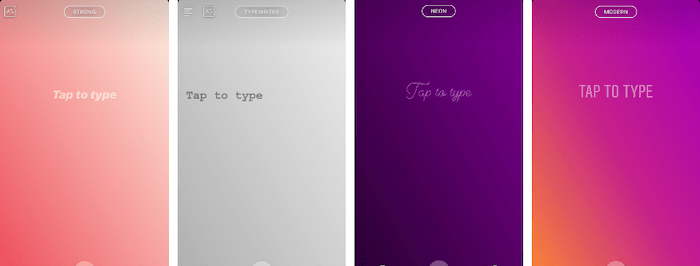
Sin embargo, Instagram regular, incluido su nombre, biografía, subtítulos y comentarios, solo tiene una opción.
Cambiar la fuente de Instagram puede ser una decisión personal o una elección de marca. Instagram en general es excelente para crear un portafolio de marca cohesivo, pero no poder hacer coincidir tus fuentes con tu estilo visual es un obstáculo para eso.
¿Cómo personalizo mis fuentes de Instagram? ¿Qué pasa con las fuentes bio de Instagram?
Te sorprenderá lo súper simple que es esto.
Ya sea que desee cambiar sus fuentes en su biografía, subtítulos y comentarios de Instagram o si desea personalizar sus Historias, lo tenemos cubierto.
Cambiar su fuente para Instagram: por qué y cómo
Como Instagram no viene con esto incorporado, usará una aplicación o herramienta de terceros para cambiar las fuentes de Insta.
La herramienta real que elija no importa tanto. No hay uno que sea particularmente mejor o peor que los demás. Algunos de los sitios web incluso tienen el mismo aspecto: compare LingoJam con las fuentes de Instagram, por ejemplo.
Con estas herramientas, una vez que esté satisfecho con el aspecto de su texto, simplemente copie y pegue en Instagram para actualizar su nombre, biografía, pie de foto o comentario.
Las mejores herramientas y aplicaciones en línea para cambiar sus fuentes IG
1) LingoJam: basado en la web
Tomé el título de mi última publicación de Instagram para jugar con LingoJam. Pegué el título en el cuadro de la izquierda y luego el cuadro de la derecha se completó automáticamente con las diferentes fuentes que podía usar.
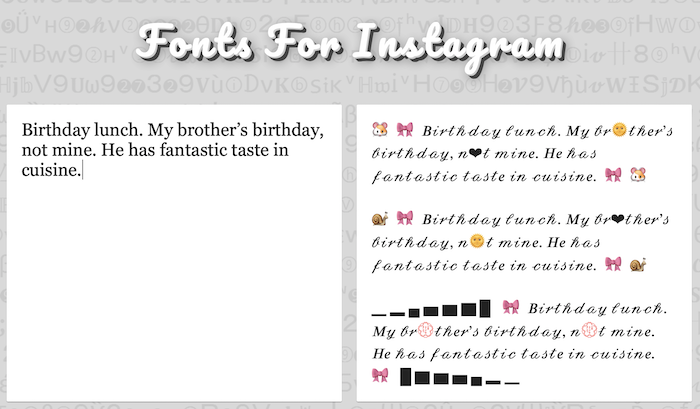
Había un montón de opciones; algunos eran tradicionales y otros eran creativos o... raros.
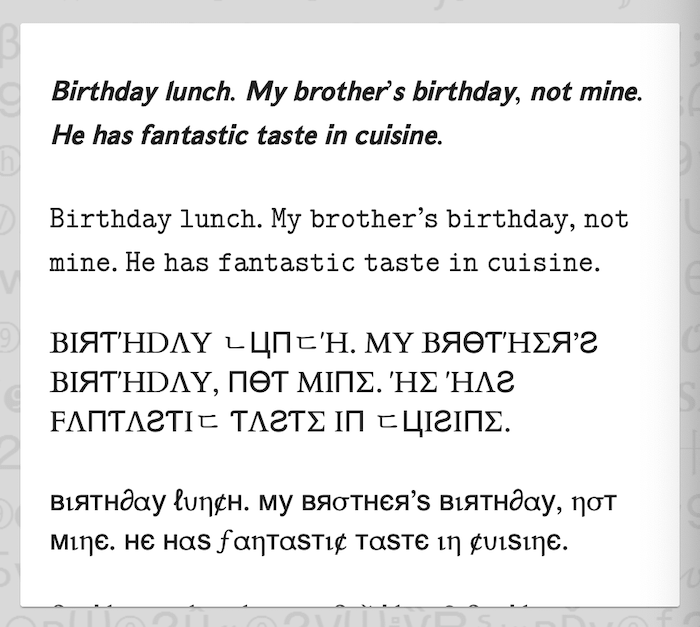
Elegí uno y lo copié/pegué como comentario en mi foto. Se veía igual en la aplicación.
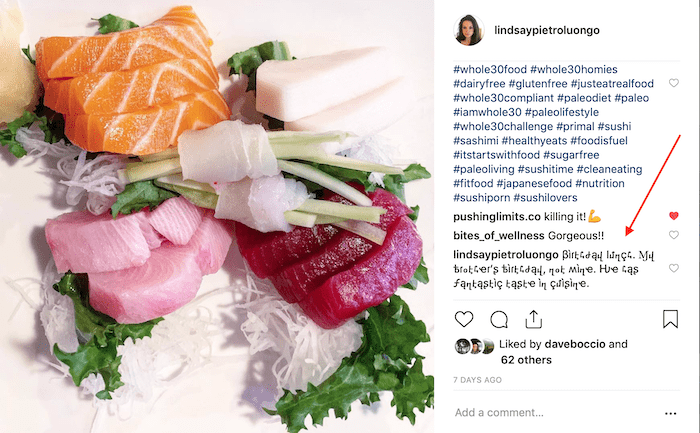
2) Fuentes de Instagram: basadas en la web
Las fuentes de Instagram funcionaron igual que LingoJam, y la selección de fuentes parecía la misma; puede haber algunas diferencias, pero nada me llamó la atención mientras me desplazaba.
Decidí cambiar mi biografía de Instagram usando el sitio web. Funcionó y se veía idéntico en línea y en la aplicación.
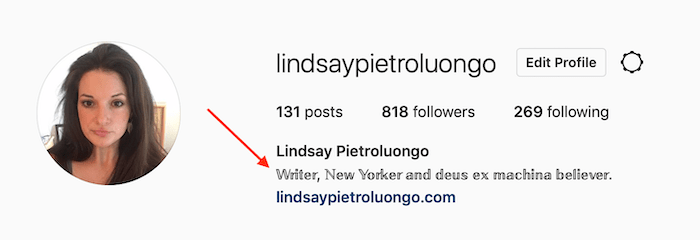
También cambié la fuente de mi nombre Insta:
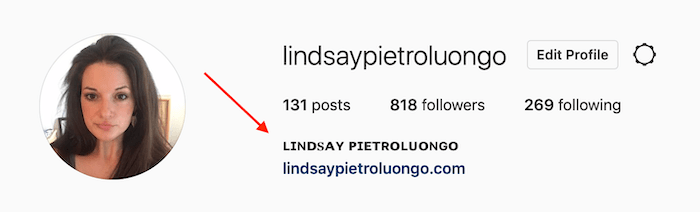
3) Mega Cool Text: basado en la web
Mega Cool Text tiene un conversor de letras chinas. Solo confiamos en que las letras sean precisas, pero se ven geniales y hay algunas opciones diferentes.
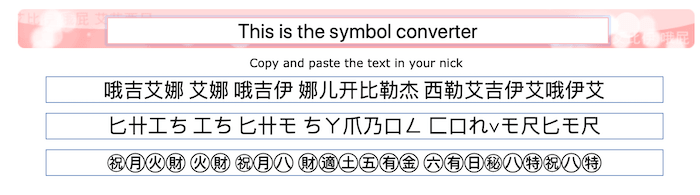
El problema con estos cambiadores de fuentes basados en la web es que es una molestia usarlos en su teléfono. Puede ir y venir de la URL en su teléfono, pero creo que usar una aplicación móvil es mucho más fácil.
4) Fuentes – para Instagram: aplicación móvil
Descargué la versión gratuita de 'Fuentes para Instagram' para ver si era más fácil de usar en mi teléfono que en los sitios web.
Con la aplicación, el proceso ocurre al revés: elige la fuente que desea y luego escribe el texto. Esto le permite crear texto que combina varias fuentes. También puedes agregar emojis.
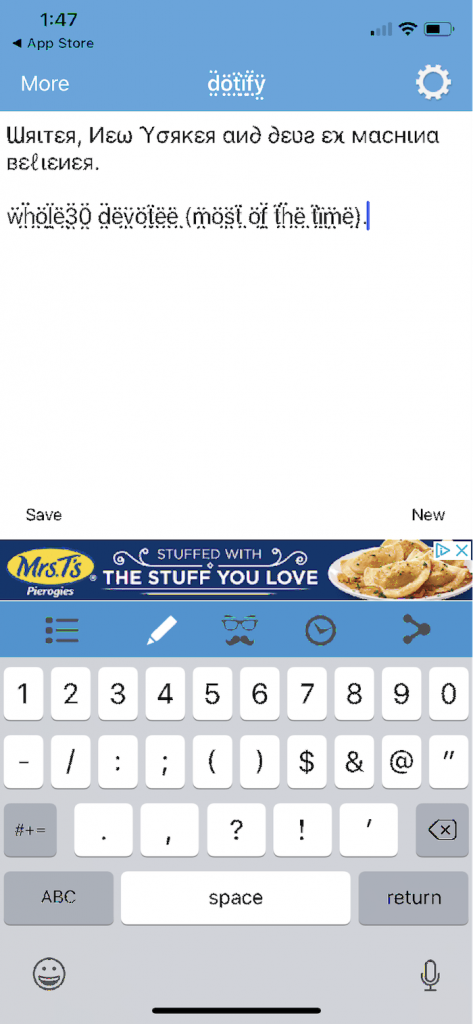
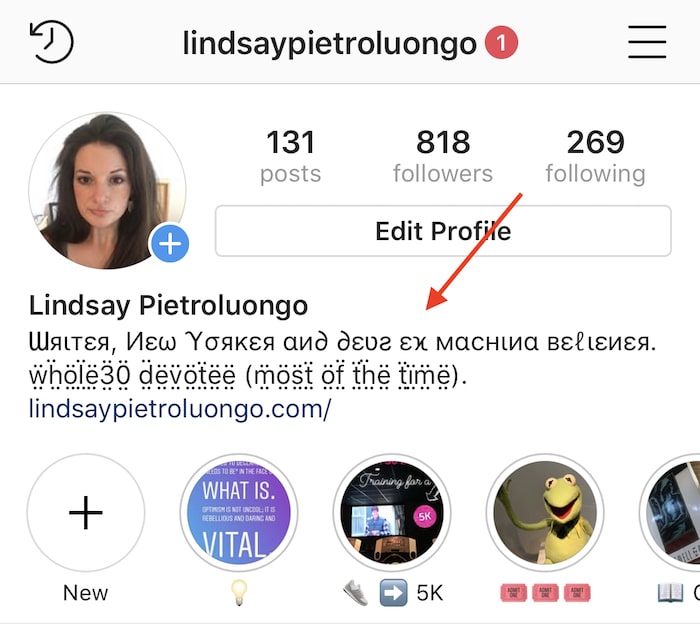
La ventaja de las aplicaciones móviles frente a un sitio web : son más intuitivas y menos complicadas de usar. También hay una forma más de acceder a esta funcionalidad, descargando una aplicación de teclado.
Ok, en otra aplicación Insta Fonts...
5) Sprezz: teclado personalizado
El teclado personalizado Sprezz es posiblemente el método más fácil para usar diferentes fuentes en Instagram, pero las opciones son muy limitadas. Sprezz es gratis y una vez que lo descargas tienes que actualizar tu configuración.
Luego puede elegir el teclado Sprezz cuando esté en Instagram tocando este símbolo:
Solo hay cinco opciones de fuente, pero solo elige tu favorita y luego la usas para escribir. Usé este estilo de fuente para cambiar mi biografía. Sin embargo, no salió en color como pensé que lo haría.
Cómo agregar símbolos a tu texto en tu biografía de IG
Digamos que desea agregar símbolos a su fuente pero quiere algo más que los emojis en su teclado. Dirígete a CoolSymbol.com en el navegador de tu teléfono, elige tu símbolo, haz clic en el botón de copiar a la derecha y luego pégalo en tu Instagram. (¡Se trata de copiar y pegar!) Agregué estrellas a mi nombre:
Deje que su texto hable más que palabras
Instagram puede ser una plataforma visualmente pesada, pero puedes completar tus publicaciones proporcionando descripciones inteligentes, perspicaces o informativas. Elegir diferentes fuentes puede comunicar más sobre su empresa y la audiencia que desea atraer.
¿Has usado las fuentes de Instagram de manera creativa? ¡Dinos en los comentarios!